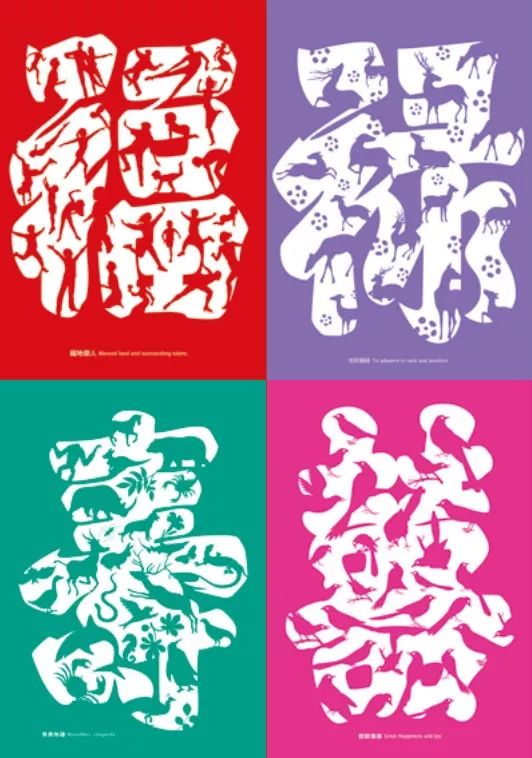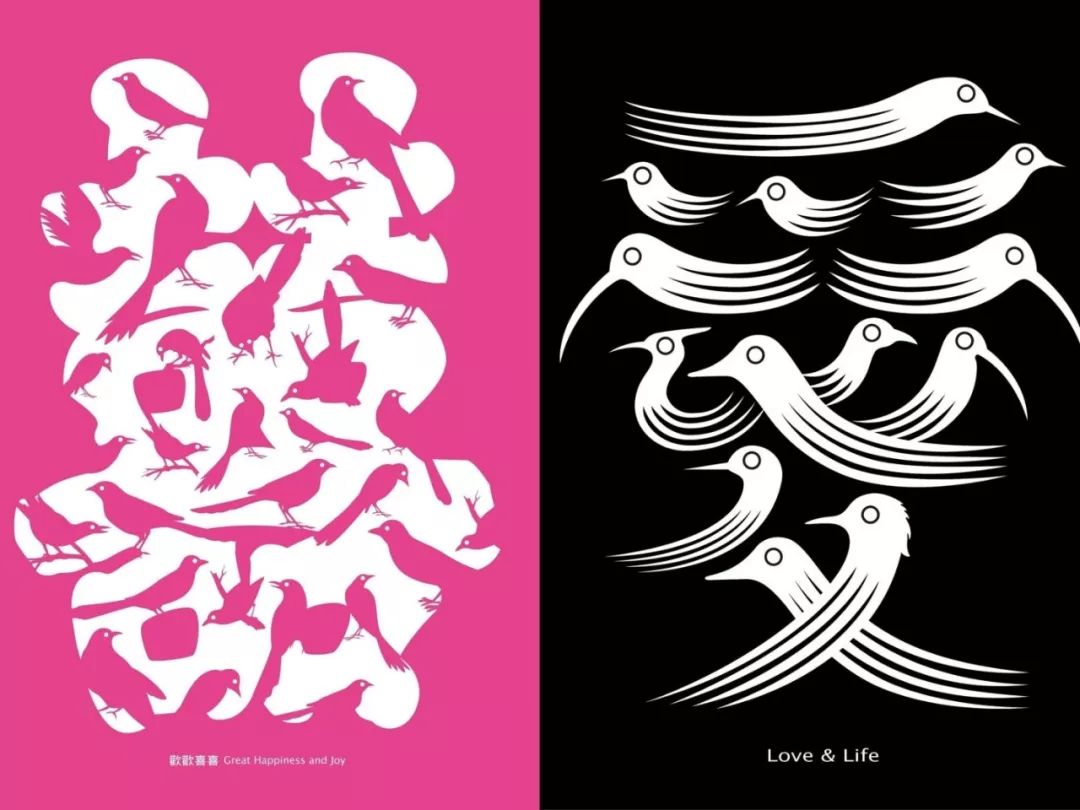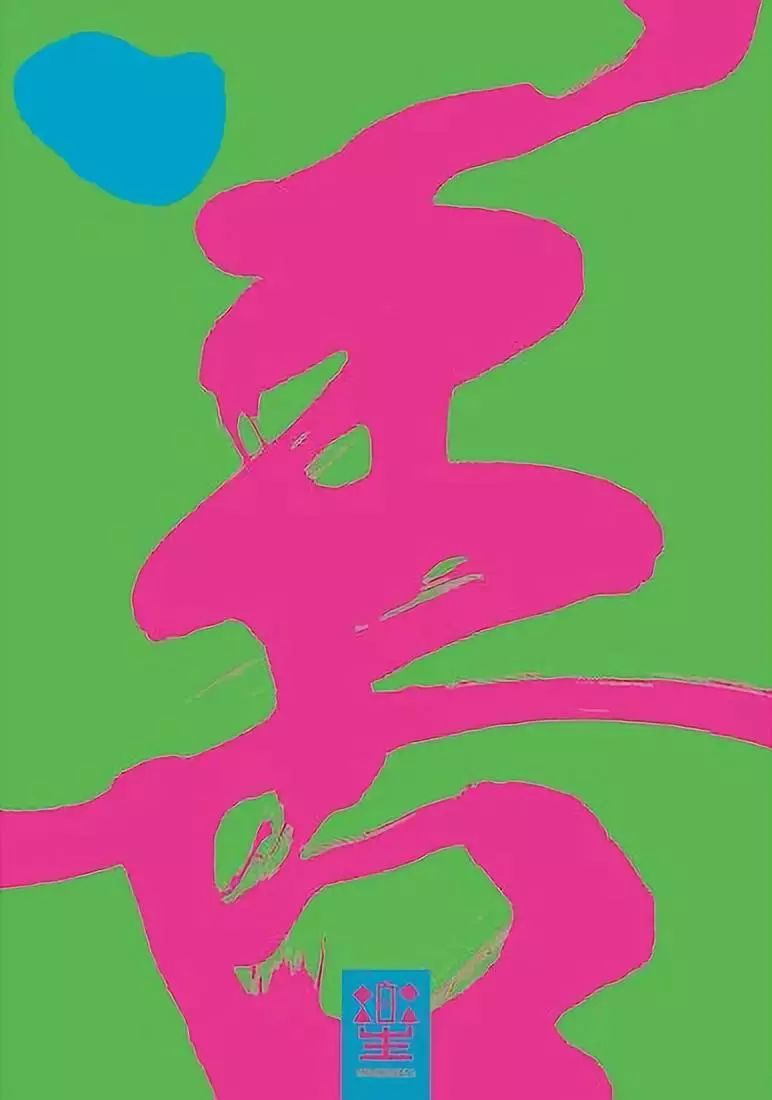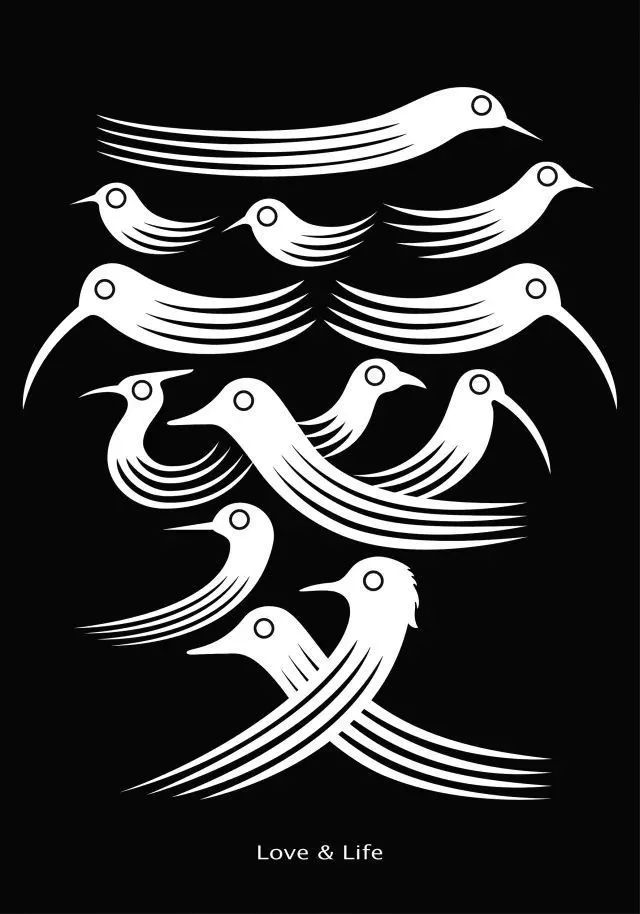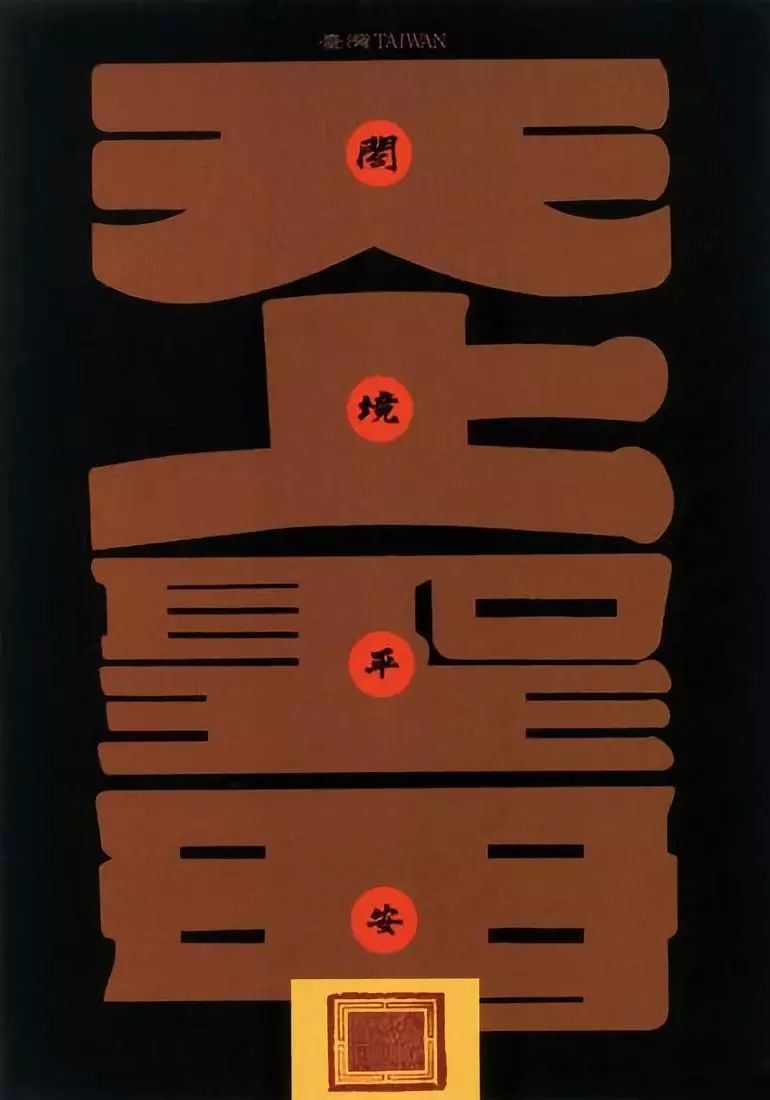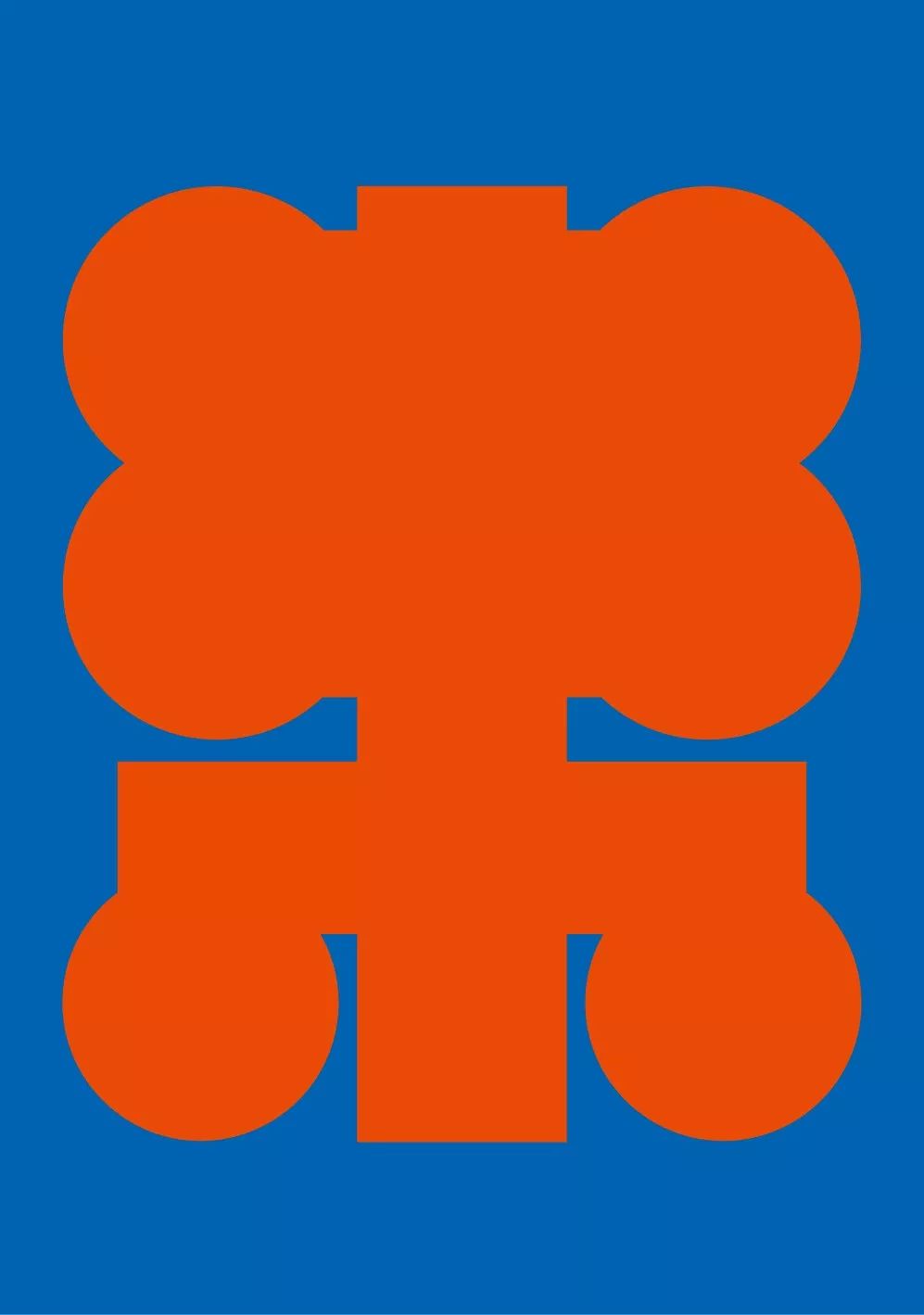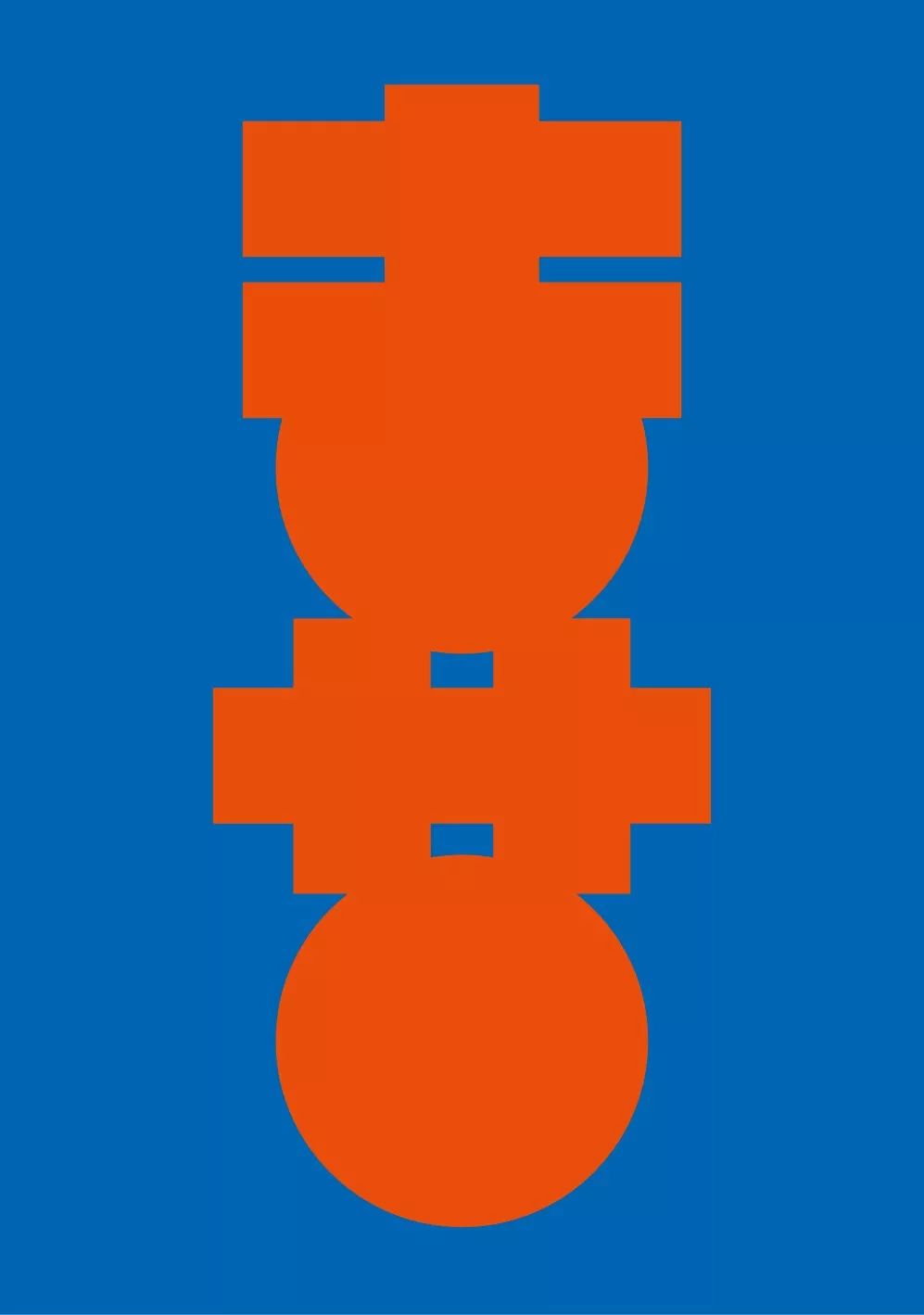
游明龙的时尚文字风景
游明龙
时尚文字风景
—
汉字の创意与时尚感
历经数千年的承传和演变,汉字在不同时代与文化的冲击下,仍能历久不衰,保持其独特性,并被各地的人们广泛使用,成为世界上最古老的文字之一。
这个独一无二的文字系统,每一个字从最初的单一意思发展至今时今日的多重意义,承载着不同年代和民族的意识形态与思维,让我们游走于其独有的视觉元素和充满趣味的文化符号世界里。而汉字在当今时代的存在价值,以至衍生出的美学,更是值得被深入探讨。
汉字设计所展现的并不是单纯的字型外观,它们具有时代感、紧扣生活脉搏,并赋予汉字在当代时空下新的意义和联想。
Yu Ming Lung|游明龙
游明龙( yu Ming Lung)台湾知名设计师,1957年生于桃园平镇,毕业于国立台湾师范大学美术学系设计组,1991年与大学同学开始从事海报创作,成立「台湾海报设计联谊会」开始崭露头角,他以满腔创作热情投入台湾这块土地,从自身文化、成长经验思考创作题材,例如将汉字图像化融入设计、以设计表达对生存议题关注、透过海报设计展现对生命关怀与人文思维。
妙法自然系列|和、美、气、真、逸、善
对于传统文化元素的理解与应用上,尤其透过现代设计手法所呈现的时尚美学,将台湾民俗、人文内涵等以视觉国际化的语言来创作概念。被喻为台湾印象与气味的传递者。并致力于海报视觉艺术创作,作品运用台湾的图像与色彩,表现洗鍊的大器与现代简约风格,展现对心灵故乡的热爱、对文化底运的追求及对生命的关注等不同主题的呈现。让我们感受汉字设计带来的魅力。
妙法自然-真
妙法自然-善
妙法自然-美
游明龙的设计创作上主要有三种形式;除了为商业品牌所设计的形象美学外,主要著重在汉字造形、台湾印象及生命关怀等人文主题,跳脱一般设计师只关注在现实议题的印象。他的平面设计充满现代主义的面貌,以简洁、精炼但深具内在象徵精神的手法,贯穿所有主题,形成独树一格的创作表现。
Love & Life愛
文字风景|春雨
文字风景|冬雪
文字风景|喜
文字风景|乐
他的作品常以「汉字」设计为题材,不论在文字造形或内涵上,都具有当地文化的亲切感,图像及色彩则有现代简约风格的美感。
欢欢喜喜
万寿无疆
从民间的美术字或汉字图案中结合工艺与造型,融入于日常生活里,让文字的情感更浓厚,更有生命的温度感。
天上聖母
1991金馬獎-影
淡泊名利
汉字的造型设计工作,一直被他认为最重要的设计课题,从书法形式、意匠文字到简约的当代时尚,努力将视觉美学运用到汉字设计的任何可能里。
汉字图案或是汉字设计曾经有一段时间不受重视,甚至被冷落。如今再度受到青睐,在商业美术设计领域大放异彩,经由设计师的杰出创作下,可谓百花齐放、百家争鸣!
除此。游明龙更喜欢将汉字设计,当作纯粹艺术来看,以视觉设计为基础,透过多媒材的应用,将平面静态形式改为立体、动画及装置方向,让文字成为人间美丽的风景!